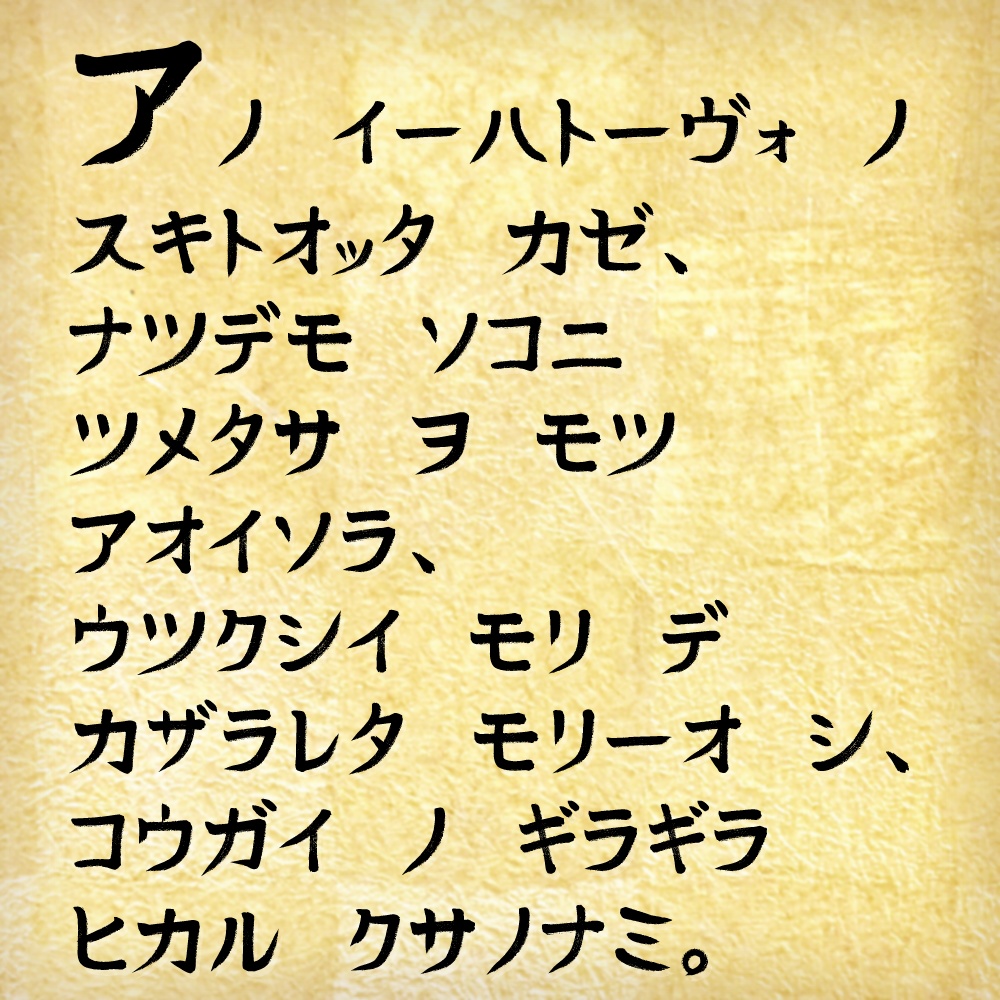
【Free】筆文字風 手書きフォント『アラミタマ』
筆文字風の手書きフォント『アラミタマ』(Aramitama)です。 筆跡や文字のかすれ具合、力強さが特徴的。クセが強いので本文よりもデザイン用途向き? 荒削りな点もありますが、字間や文字サイズを調整しつつ、上手にご活用いただければ幸いです。
収録文字
・カタカナ ・数字 ・一部記号(ー、。!?) ひらがな、アルファベットは後日追加予定。 その他文字の追加・修正は反響とやる気次第となります💪💪